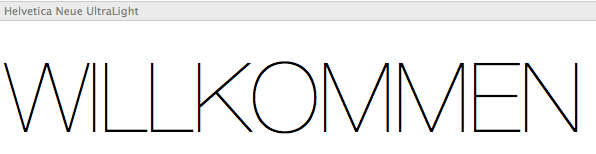
Ebay fashion outlet schrift
wie heisst die schrift die auf der neuen ebay werbung zu sehen ist?????, direkt auf ebay.com ebay fashion outlet, ist das helvetica?
Helvetica ExtraFrein aus der Helvetica Neue kommt gut ran würde ich sagen.
Pomeranz, genau die meine ich! helvetica extra fein kommt hin, aber da ist irgendwie ein leichter strech drin
Also meine Neue Helvetica Ultra Light ist schon deutlich anders als diese da.
Siehe z.B. W, K, O, M, E
Ja, und das B stimmt auch nicht ganz überein. Aber eine Schrift, die näher dran kommt als die Ministry habe ich nicht finden können. Vielleicht hilft das leesummer ja etwas weiter bei der Suche.
Die Alright Sans kommt auch dicht dran. Da ist das O runder, aber das K stimmt immer noch nicht ...